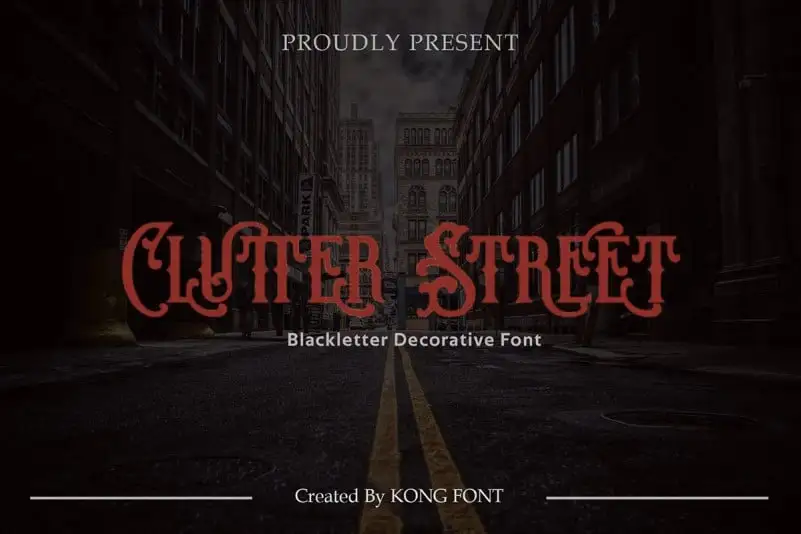
Introduzimos Clutter Street Display Font, uma elegante fonte de rótulo vintage. Esta tipografia se destaca quando usado junto à escrita, mas brilha ainda mais com títulos de exibição, logotipos e outros elementos visuais. A fonte inclui muitas alternativas para letras maiúsculas e minúsculas, além de alternativas para as letras maiúsculas e várias alternativas para letras minúsculas. Esses ajustes permitem que você faça sua criação mais expressiva, variada e divertida, permitindo criar inúmeras opções para seu design. Além disso, use ornamentos para complementar seu trabalho de design. Clutter Street Display Font é uma escolha ótima se você está procurando por uma fonte que adiciona um toque vintage ao seu design.